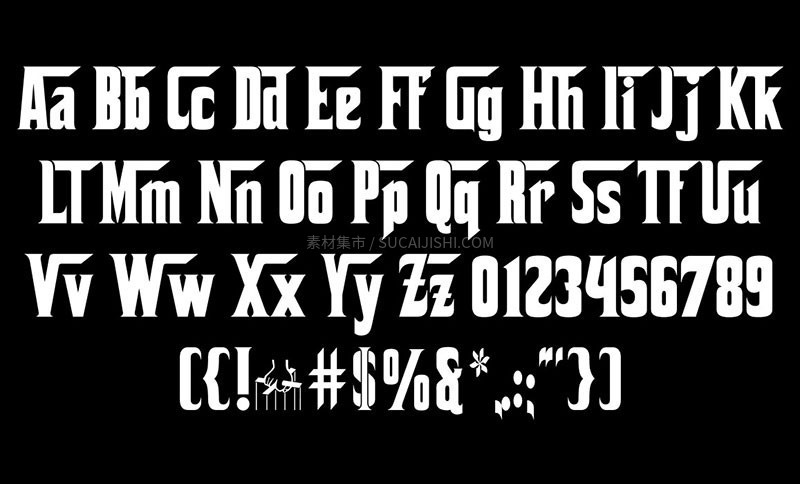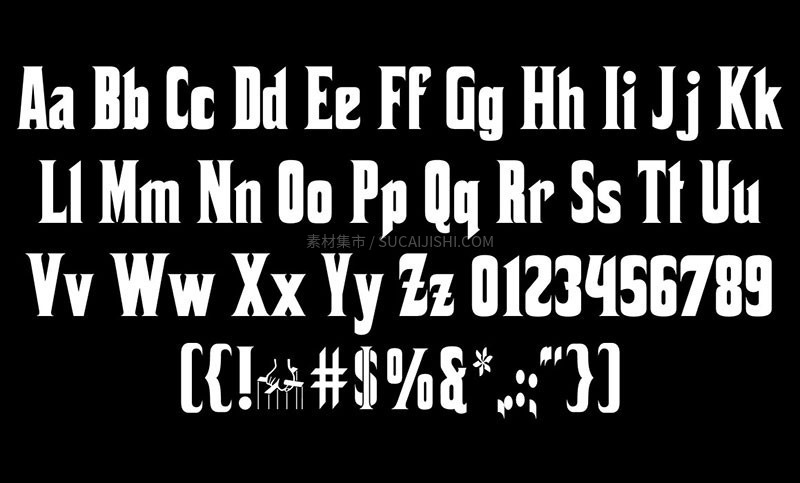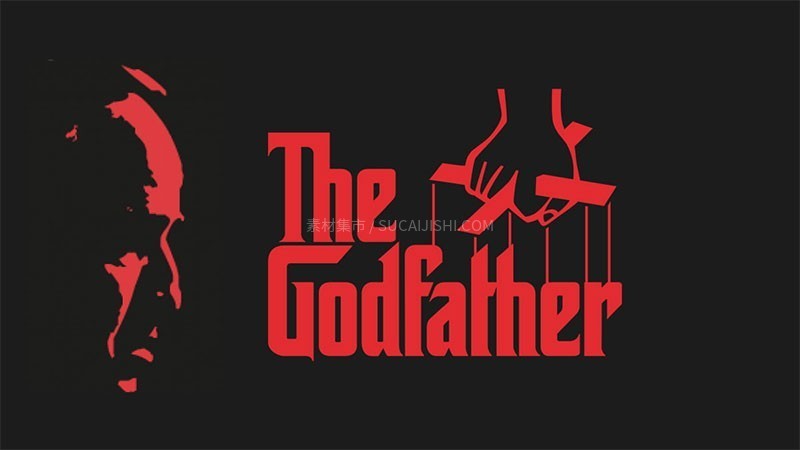
经典黑帮史诗《教父》同名复刻字体:Corleone
《教父》(The Godfather)是弗朗西斯·福特·科波拉执导的影史巅峰之作,深度刻画了科里昂家族在犯罪、忠诚与背叛交织下的传奇崛起。FontMesa 特别将电影标志性的视觉风格复刻为 Corleone 字体,完美重现了那份沉稳、威严且极具辨识度的经典质感。